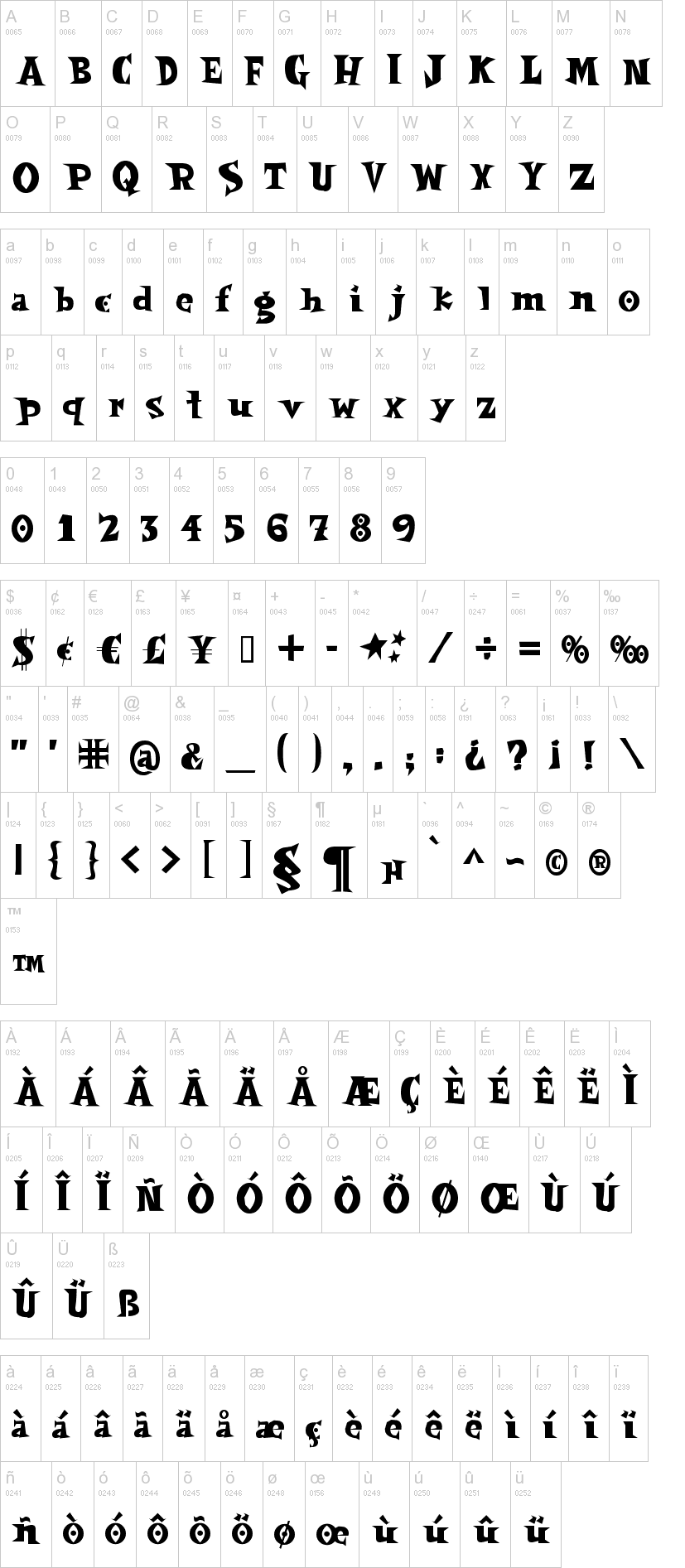
Spooky Magic
Spooky Magic是一款具有恐怖氛围的魔法字体,由著名设计师Maelle.K创作。这款字体的特点是混合了欧洲和美国的魔法风格,有着古老的古怪气息,集合了恐怖、魔法、和古典的元素,并且拥有精美的符号和大量的变体。它的非常适合用于广告、品牌标志、漫画书、封面、海报等等。
Spooky Magic是一款非常不错的手写艺术字体,具有很好的视觉感,适合于文化类的宣传设计、商业类品牌的广告和产品包装设计以及个性化文字排版等较多场景。
Spooky Magic字符映射图